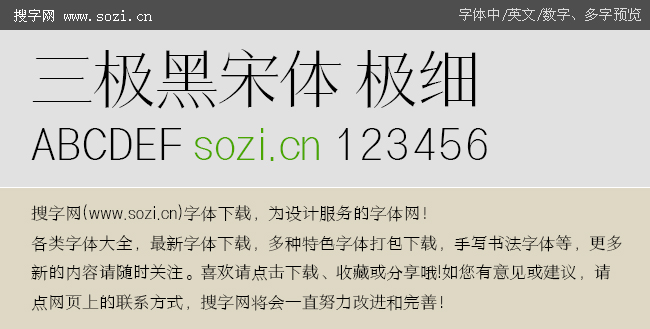
三極黑宋體 極細
搜字網(wǎng)給大家提供一款三極黑宋體 極細中文字體下載,三極黑宋體是一款現(xiàn)代與古典相結(jié)合的簡約風(fēng)宋體,筆畫上橫細豎粗,細節(jié)上做斜切處理,干凈利落,在不缺乏古典美的同時擁有著現(xiàn)代風(fēng)的創(chuàng)意設(shè)計。適用于平面宣傳設(shè)計、網(wǎng)頁設(shè)計、海報設(shè)計等應(yīng)用。